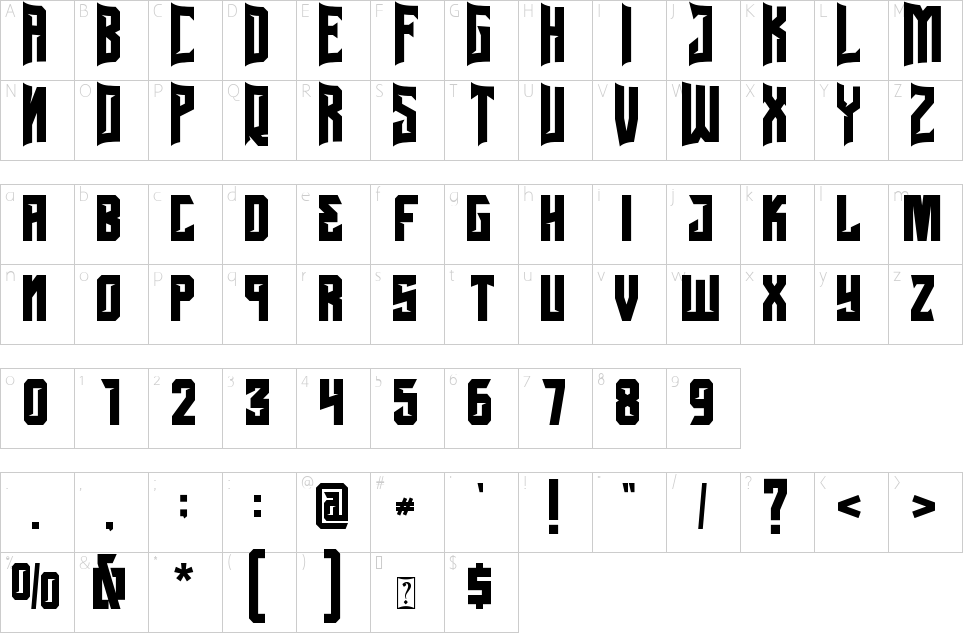
Através do site Grandover Font – 1001 Free Fonts, você pode encontrar uma grande variedade de fontes gratuitas que podem ser utilizadas tanto no Windows quanto no Mac. Esta página é um ótimo lugar para quem busca estilos únicos e interessantes sem gastar dinheiro extra. Um dos destaques da fonte é a Grandover. Desenhada pela Letterara Studio, esta fonte oferece uma escolha incrível de letras e números, que vão desde textos clássicos até mais modernos e contemporâneos. Combinadas com um design cuidadosamente elaborado, as Grandover podem ajudar qualquer projeto a ser chamativo e único. Para quem está em busca de fontes gratuitas para suas necessidades, esta é uma ótima opção. Grandover não só oferece estilos variados como também tem sido baixada 395 vezes por outros usuários do site. É um investimento em seu trabalho gráfico que vale a pena ser feito. Aproveite este rico leque de opções para tornar seus projetos ainda mais expressivos e personalizados.